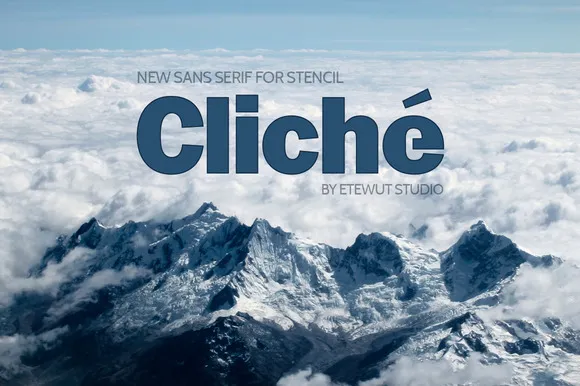
A fonte Cliché Typeface é uma elegante escolha para designers que procuram estêncil design com estilo moderno. Suas linhas retas e clean são perfeitas para trabalhos impressos, seja por meio de corte a plotter ou impressão digital. Você também terá facilidade em usar essa fonte para multi-línguas, incluindo o russo. Este é um recurso ideal tanto para marcas quanto para identificar produtos físicos e digitais. Sua versatilidade significa que você pode assinar tudo o que quiser, então não tenha medo de experimentar! A Cliché Typeface é uma ótima escolha se você está procurando por uma fonte sans serif moderna e fácil de usar.